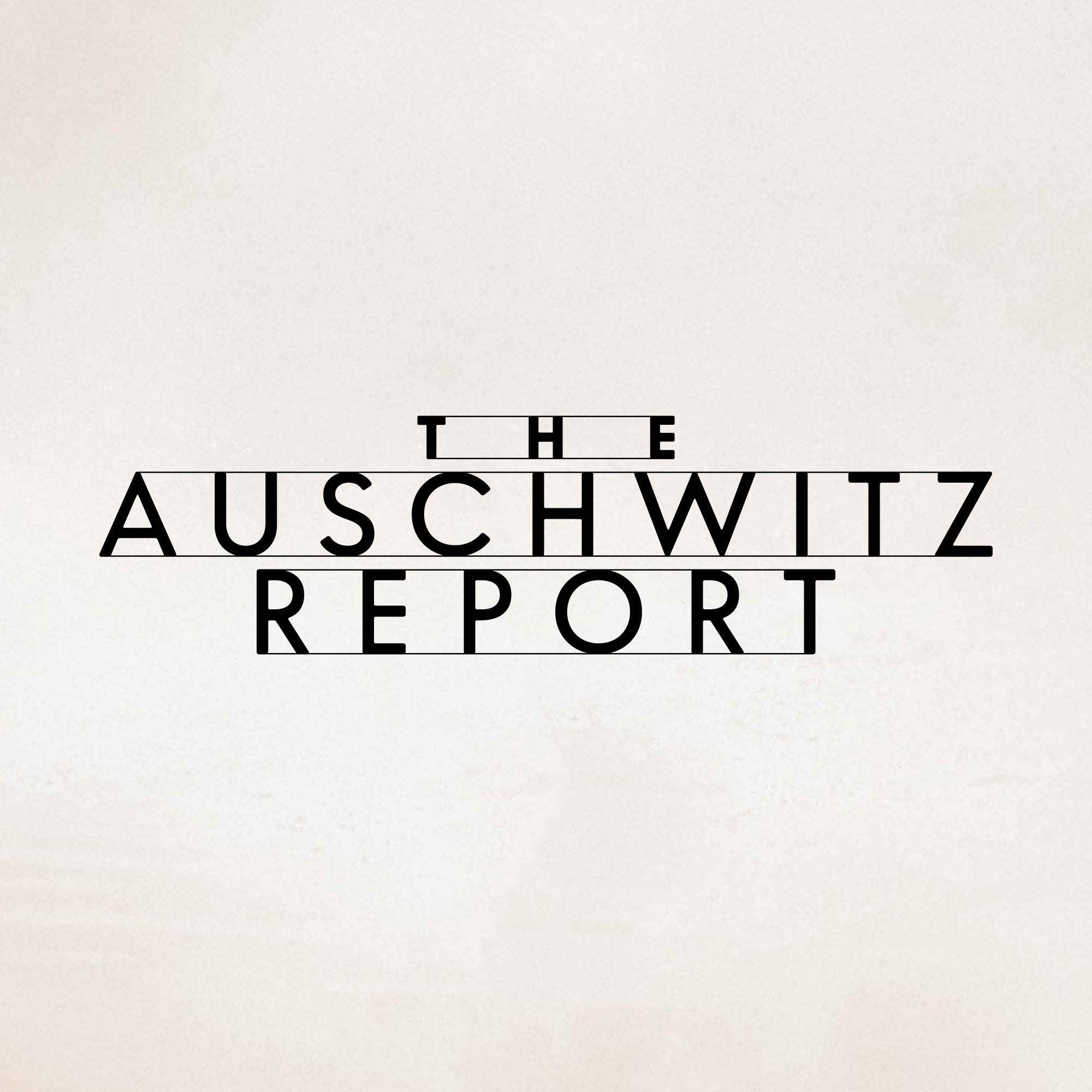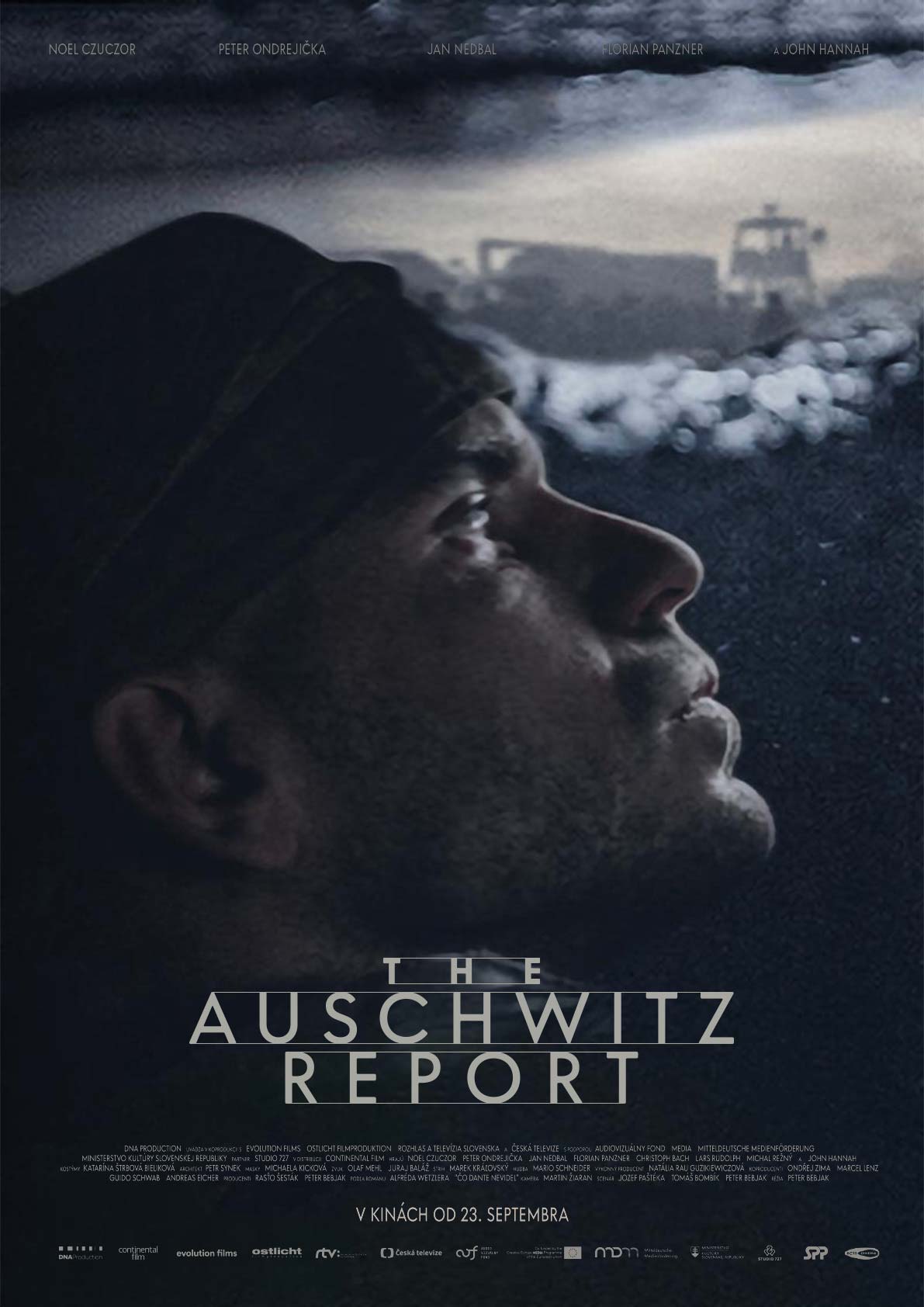
Správa
Logo pre film Správa, inšpirovaný nápisom Arbeit Macht Frei z brány koncentračného tábora Auschwitz, v ktorom sa odohráva príbeh filmu.
V logu je použité zatiaľ nepublikované písmo Ocarina, v ktorom boli upravené medziznakové medzery a vyladené niektoré detaily tak, aby znaky dobre fungovali so spojovacími linkami. Pre slovenskú a českú verzii názvu bola navrhnutá aj nová diakritika v súlade so zvolenou estetikou.